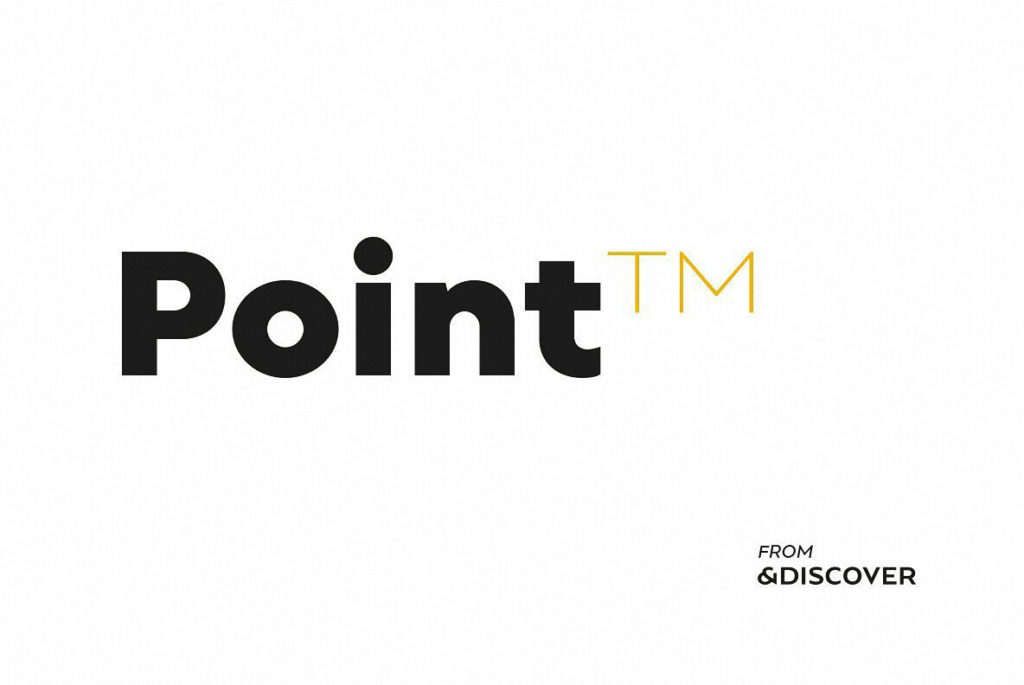
Шрифт Point
это геометрический гротеск от автора Владимира Набокова, отличающийся строгими формами букв и минималистичным дизайном. В основе гарнитуры лежат математически выверенные линии и круги, что придает ей технологичный и современный вид. Шрифт полностью адаптирован для набора текстов: поддерживается кириллица, латиница и другие языковые наборы. Благодаря нейтральному характеру и высокой читаемости, он отлично подходит как для создания логотипов, так и для оформления веб-интерфейсов. Скачать бесплатно версию с поддержкой кириллических символов можно в разделе загрузки ниже.